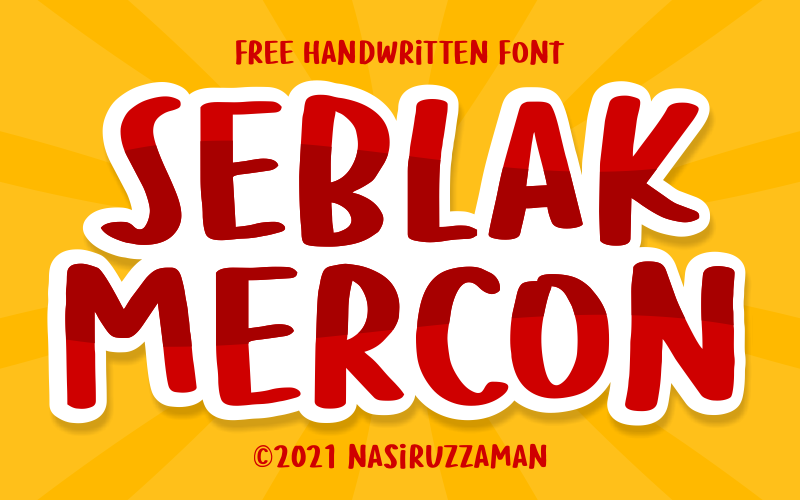
Seblak Mercon Font – Download Grátis
A Seblak Mercon Font é uma elegante tipografia display ideal para quem busca adicionar um toque atraente e sofisticado às suas criações digitais. Com seu design minimalista, a fonte transmite elegância e força ao mesmo tempo, tornando-a perfeita tanto para projetos de marca quanto para logomarcas, convites de casamento, postagens nas redes sociais, publicidade, embalagens de produtos, designs de produto, rótulos, fotografias e até mesmo marcas d’água. Seblak Mercon é uma fonte poderosa que capta a atenção do seu público alvo com suas linhas definidas e seus desenhos leves que adicionam um brilho especial aos seus projetos visuais. A sua versatilidade faz dela uma escolha inteligente para quem quer criar designs multifacetados e de alta qualidade, não importa o propósito do projeto em questão.